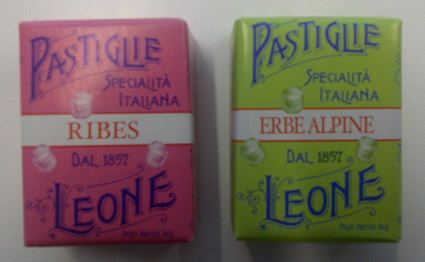
Ein Süßwaren-Klassiker aus Italien, ja, die Originale gab's noch in einer Blechbox.
Der Produktname (Pastiglie Leone) ist ja wohl »von Hand gestrickt«? Oder doch nicht?
Weiß wer Rat, kennt wer Ähnliches?
mit sicherheit handgemacht, aber es gibt ähnliche fonts,
und mit etwas handarbeit bekommt man ähnlich ergebnisse sicherlich hin.
ähnliche schriften findest du mit sicherheit auch hier:
Ich würde handgeblasen und mundgemalt behaupten. Ähnliche Schriften gibt es schon.
Mach mal eine Google Bildersuche mit folgenden Stichworten: "Art Nouveau" Fonts
Dann bekommst Du ganz viele Bilder von teilweise ähnliche Schriften vorgeworfen.